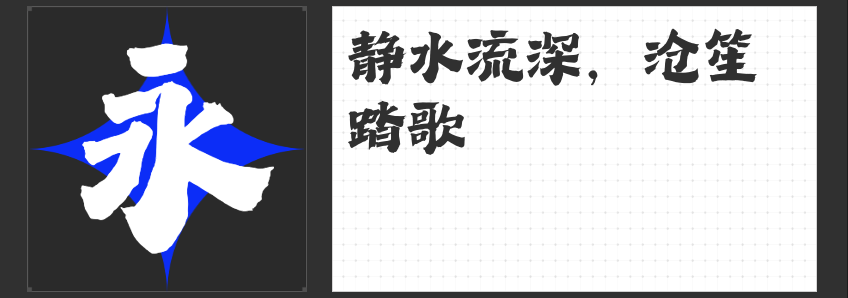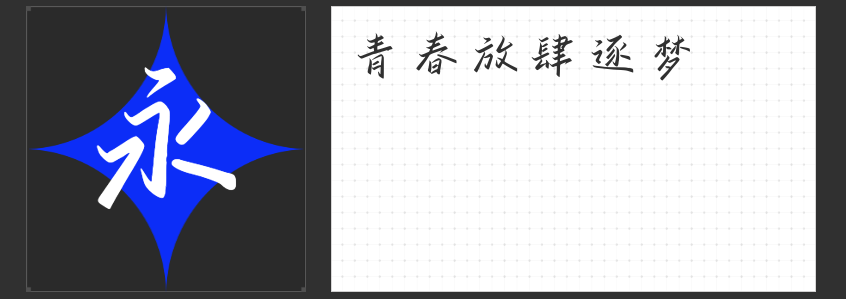
音乐与视觉的碰撞:四款精选字体打造独特专辑封面
专辑封面不仅仅是歌曲内容的载体,更是艺术家个性与情感的表达方式。一个好的封面设计能够瞬间抓住听众的眼球,激发他们的好奇心。今天,我们就为大家推荐四款适合专辑封面设计的字体。这些字体各具特色,能够为不同风格的音乐作品带来独特的视觉效果。
1. 励字暴风简 超级黑 —— 摇滚乐的力量象征
“励字暴风简 超级黑”是一款现代创意型黑体,字型厚重带一些开放性。这种字体非常适合用来做一些摇滚风格专辑封面的标题设计,其厚重而略显开放的笔触给人一种强烈的视觉冲击力。无论是重金属还是朋克,这种字体都能够完美地表达出摇滚乐的精神内核,吸引人眼球的同时,也能传递出歌曲背后的深层含义。
2. 造字侠热辣隶简 —— 古风与复古的完美融合
“造字侠热辣隶简”是一款结合了传统隶书特点与现代设计元素的创意隶书。这款字体非常适合用于制作古风、复古、庄严风格专辑的封面。其线条流畅、笔画饱满,给人以强烈的复古感,能够为专辑增添一份庄重与神秘的气息。它不仅能够将听众带入一个遥远而又迷人的时代,还能让人感受到音乐作品背后深厚的文化底蕴。
3. 万人字造踏歌行体 —— 国潮风格的独特魅力
“万人字造踏歌行体”是一款很有个性的毛笔字体,其笔画流畅自然,充满艺术气息。这种字体非常适合用于一些国潮风格的专辑封面设计。它能够在保持传统美感的同时,融入现代设计理念,使封面设计既古典又不失时尚感。无论是流行音乐还是传统民乐,这种字体都能为作品注入一股独特的东方韵味。
4. 字青春逐梦简 准粗 —— 青春记忆的美好记录
“字青春逐梦简 准粗”是一款文艺手写字体,笔触自然流畅,充满生活气息。这种字体非常适合用于关于青春、回忆、恋爱歌曲的专辑封面设计。它能够唤起人们对美好时光的回忆,给人一种温馨而怀旧的感觉。使用这种字体作为封面设计的一部分,不仅能够体现出歌曲的情感内涵,还能让听众在欣赏音乐的同时,感受到那份青涩而美好的岁月。
字体虽小,却能在专辑封面上发挥巨大的作用。上述四款字体各具特色,能够满足不同音乐风格的需求,帮助艺术家们更好地表达自己的创意与情感。希望您在下一次设计专辑封面时,能够从这些字体中找到最适合的那一款,为听众带来一场视觉与听觉的双重盛宴。